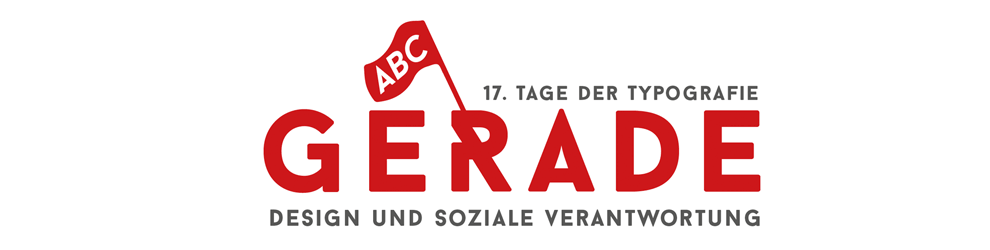
17. Tage der Typografie in BerlinGERADE – Design und soziale Verantwortung
Typografie- und Design-Workshops vom 2. bis 4. September 2016 in Berlin
Gerade und kursive Schriften ergeben einen Kontrast und gleichzeitig ergänzen sie sich in der Gestaltung ebenso wie die Kombination von Geraden und Kurven. Buchstaben haben gerade und runde Formen und ergeben im Zusammenwirkung diese Form.
In der Tradition der Tage der Typografie steht »Gerade« nicht nur für typografische Aspekte, sondern auch für soziales und gesellschaftliches Engagement, für das wir uns gerade machen. Und wer sich gerade für etwas macht, sich für etwas einsetzt, lehnt sich gegen etwas (auf).
Bei den diesjährigen Tage den Typografie wollen wir die soziale Verantwortung von Designer/innen mit ihrer Arbeit in den Vordergrund stellen. Als Mediengestalter/in, Grafikdesigner/in, Fotograf/in geht es nicht nur darum Dinge »schön« zu machen. Wir haben die Möglichkeit mit unserer Form auch Inhalte, die weit über eine Werbeaussage hinausgehen, zu visualisieren und zu transportieren.
In den Vorträgen und Workshops bringen wir fachliche Weiterbildung und soziales Engagement zusammen.
Die 17. Tage der Typografie finden vom 2. bis 4. September erstmalig in der gewerkschaftlichen Bildungsstätte Clara Sahlberg in Berlin-Wannsee statt.
Die Workshops
Der typografische Tausendsassa Dirk Uhlenbrock, (Erste Liga, Essen) zeigt in seinem Workshop wie Mit einfachsten (typo)grafischen Mitteln eine klare, einprägsame Aussage zu treffen ist. In diesem Workshop geht es um das Destillieren von visuellen Ideen, die Kunst der Reduktion und den Mut Dinge weg zu lassen. Petra Beiße, (handlettering studio, Wiesbaden) widmet sich der Handschrift:
Einen Schriftzug entwickeln, basierend auf der eigenen Handschrift. Wie fange ich an? Brauche ich als Basis eine »gute« Handschrift? Wie schreibe ich mich ein? Wie verändere ich meine Handschrift? Welche Möglichkeiten oder »Tricks« gibt es? … und welche Verantwortung habe ich als Schreibender? Aus Frankfurt kommen Jörg Schmidt und Martin Stiehl vom Institut für Gebrauchsgrafik. In ihrem Workshop dreht sich alles um die Frage wie man abstrakte politische Inhalte, konkret in Form von Plakaten umsetzen kann. »Mit Mut zur Abstraktion und dem Vertrauen auf die Fähigkeiten der Rezipient/innen lassen sich Gestaltungslösungen finden, die den Kommunikationsinhalten besser gerecht werden.« eter Reichard (Designmacherei, Offenbach) wird in seinem Workshop zeigen, wie versteckte Botschaften Menschen in ihrem Alltag erreichen können und verbindet Verpackungsdesign mit sozialen Inhalten. »Wollen wir Menschen mit unseren Botschaften und Themen erreichen müssen wir dort hin, wo die Menschen sind. Wir müssen die Botschaften im Alltag platzieren. Das kann mittels Aufkleber, Flyer oder Plakaten geschehen. Aber man kann sich auch anschleichen und Inhalte vermitteln auf Produkten des alltäglichen Lebens, mittels Verpackungen und Etiketten transportieren.«
Der Freitag Abend wird mit einem Vortrag zum Thema ergänzt. Der Schwerpunkt liegt in der Arbeit in den Workshops, die allesamt analog ausgelegt sind, da die Entwicklung der Idee im Vordergrund steht.